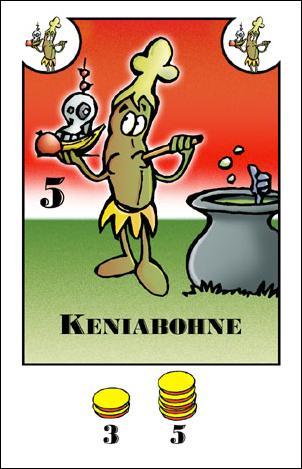
Kann mir jemand diese Schriftart nennen?
Frage oben und Bild im anhang.
Bodoni MT Black müsste es sein wobei alles groß geschrieben wurde und die Größe des ersten Buchstaben höher ist als die der anderen. Sieht zumindest für mein Auge nach dieser Schriftart aus.
Da gibt es viele ähnliche Arten. Ich Persönlich tippe auf "Bernard MT Condensed" oder "Frank Ruehl"
Ähnlich sind auch Rod,Narkisim, Miriam oder Levenim MT. Must halt mal in (wenn Du hast) Word probieren.
könnte mit „Braggadocio“ verwandt sein. Vor allem weil das „K“ genauso aussieht.
hmm die schriftart kann ich dir nicht nennen..
aber das ist bohnanza! :D